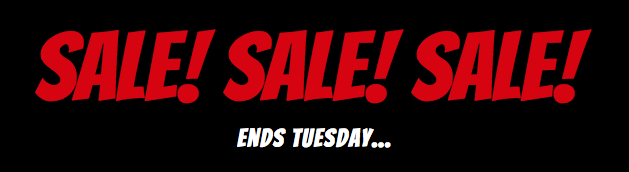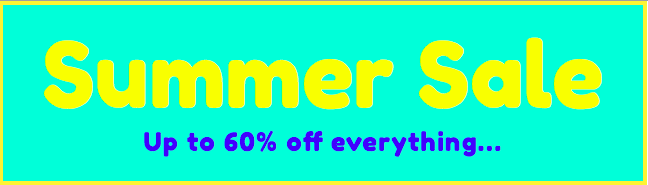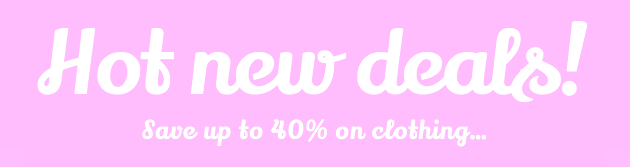
Es ist wieder soweit! Wir haben tief in unserer Font-Kiste gekramt und noch mehr coole Schriftarten gefunden, die ihr in euren E-Mail-Marketing-Kampagnen clever einsetzen könnt. Diese Web-Fonts sind alle in Mail Designer 365 verfügbar und bieten euch Inspiration für eure Designs…
Fonts für Aktionen
Sonderrabatte, Aktionen und Promotions sind wesentliche Bestandteile eurer E-Mail-Marketing-Strategie. Es ist wichtig, einen starken Font zu wählen, der eure Aktion möglichst gut hervorhebt. Wie ihr in den Beispielen unten sehen könnt: Je auffälliger die Schriftart, desto besser werden Leser auf eure Kampagne aufmerksam…
Der „Comic-Book“ Stil von Bangers ist super auffällig
Lily Script One bietet eine attraktive Mischung aus fett und feminin
Die Rundungen von Fredoka One machen sich sicher gut in eurem nächsten Newsletter
Fonts für CTAs
Jeder gute E-Mail-Newsletter beinhaltet mindestens eine Call-To-Action (CTA). Der Sinn einer CTA ist es, euren Lesern eine klare Handlungsaufforderung zu geben (was ja auch der Zweck der E-Mail-Kampagne ist). Aus diesem Grund ist es wichtig, für CTAs eine starke, klare Schriftart auszuwählen, die für eure Kunden gut lesbar ist.
Changa One ist eine moderne und auffällige Option
Nobile ist minimalistisch, aber effektiv
Mit Candal liegt das Augenmerk garantiert auf eurer CTA
Fonts für euer Business
Für Business-Profis ist es sinnvoll, eine gut wiedererkennbare Schriftart in E-Mail-Designs zu verwenden. Da Branding super-wichtig ist, hilft es euch als Unternehmer, einen Basic-Font als Grundlage für alle eure Business-Designs zu nutzen. Versucht einen Font zu finden, der mehrere Stiloptionen bietet (z.B. Leicht, Normal, Fett), damit ihr mehrere Design-Möglichkeiten habt. Für moderne Unternehmen empfehlen wir eine schicke sans serif Schriftart, wie zum Beispiel diese hier…
Encode Sans Light ist modern und stylisch
Merriweather Sans Light ist eine gute Option für Tech-Unternehmen
Tenor Sans hat einen klassischen Touch
Fonts mit Charakter
Viele Designer sind auf der Suche nach einzigartigen Fonts, die ihre Newsletter unvergleichlich machen. Besonders neue Unternehmen können von der Wahl der richtigen Schriftarten profitieren, welche den Designs einen Charakter geben…
Aguafine Script ist ein Handwriting-Font mit viel Schwung
Finger Paint ist eine gute Wahl für Schulen, Kindergärten oder andere Bereiche, die mit Kindern zu tun haben
Julius Sans One ist eine stylische und moderne Schriftart
Fonts für Feste
Es gibt wirklich einen Font für jeden Zweck. Ob ihr ein einmaliges E-Mail-Design für eure Kollegen gestaltet, oder eine besondere Schriftart für euren Halloween-Newsletter sucht: Für jedes Szenario gibt es einen Webfont. Das sind zwei coole Beispiele…
Butcherman ist der perfekte gruselige Font für Halloween-Designs
Mountains of Christmas ist eine charmante Schriftart, die super zu Weihnachten passt